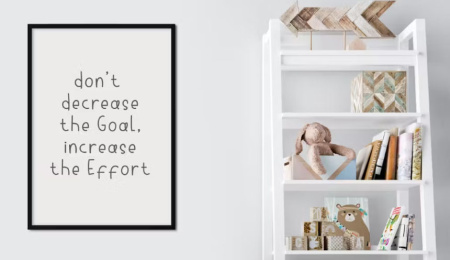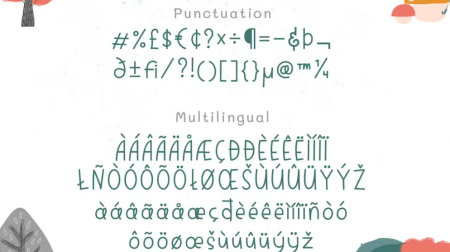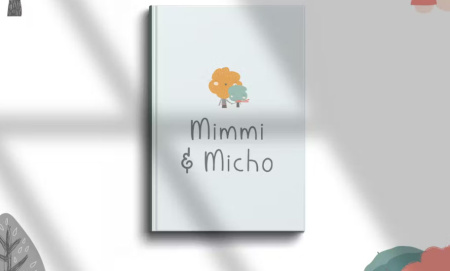
فونت رایگان انگلیسی Magical Smiles
فونت انگلیسی Magical Smiles که به صورت کاملا رایگان از جی اف ایکس دانلود در اختیار شما قرار داده شده است. یک فونت انگلیسی با طراحی بازیگوش. تک تک حروف با دقت ساخته شده اند تا متن شما زیبا به نظر برسد. با سبک منحصر به فرد مدرن، این فونت برای بسیاری از پروژه های مختلف مانند نقل قول، سربرگ وبلاگ، پوستر، عروسی، برندسازی، آرم، مد، پوشاک، نامه، دعوت نامه، لوازم التحریر و غیره عالی خواهد بود.
✅ نام فونت: Magical Smiles